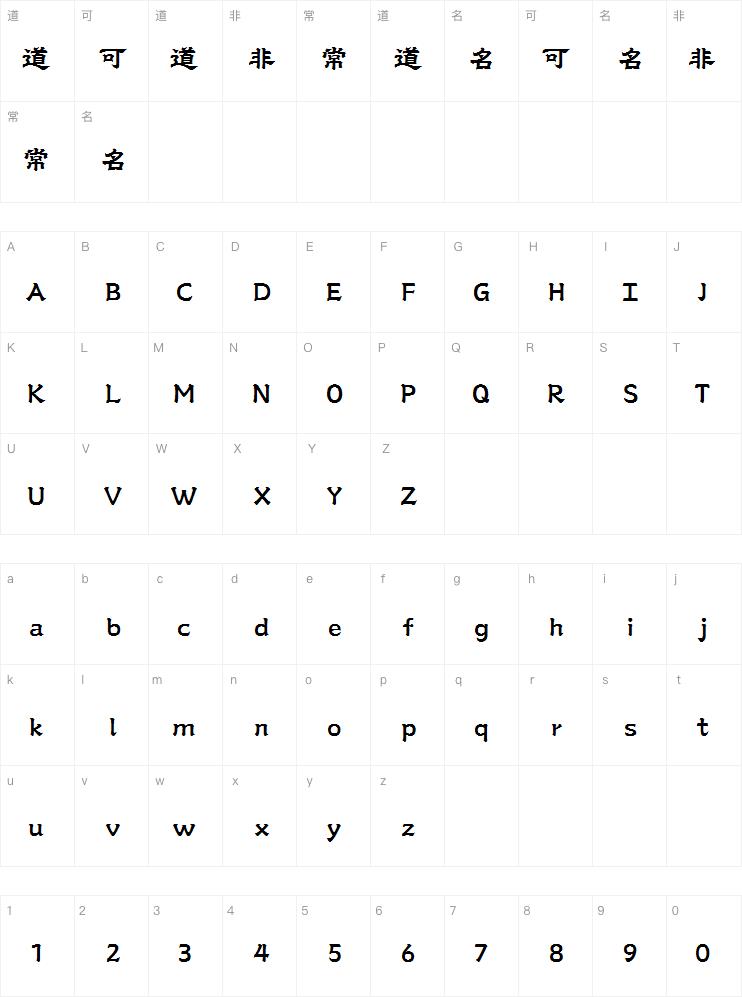
山海青山隶75W,是一款全新隶书风格的字体,是山海青山隶字体家族系列中的中等粗细款,编号75W,包含汉字9169个,符号200+个。该字体是一款具有强劲视觉冲击力的隶书风格的字体。字形结构多为方形结构,如正方形、长方形或扁方形,强调字形的稳定性和内敛精神。字形大小悬殊,通过大小不一的字来形成对比和层次感,造型硬朗,直线与曲线结合的笔画构成棱角分明、坚实有力。